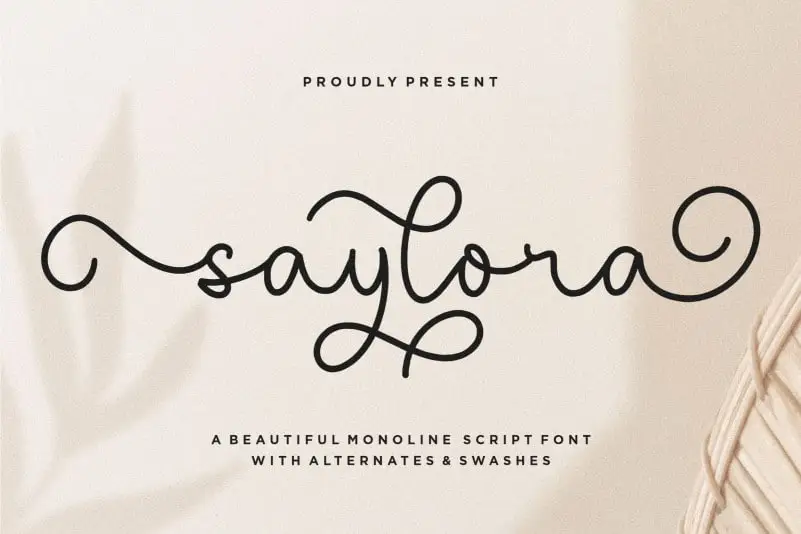
Saylora Script Font – Fonte Grátis
Saylora Script Font
A fonte Saylora Script é perfeita para criar uma identidade única, seja no design do produto ou na criação de marca. Seus traços fluidos e elegantes permitem que você personalize sua identidade visual de formas impressionantes e memoráveis. Ideal tanto para editoriais, como sites de mídias sociais e aplicativos, a fonte Saylora Script também é perfeita para projetos de casamento onde deseja destacar mensagens em destaque sobre o fundo. Com um tom suave e sofisticado, ela torna sua marca ainda mais memorável e distintiva, permitindo que você expressione suas ideias com fluidez e elegância. Ideal tanto para textos de alto nível como para pequenos detalhes destacados, a fonte Saylora Script é uma escolha inteligente se você deseja dar um toque único à sua próxima criação visual.